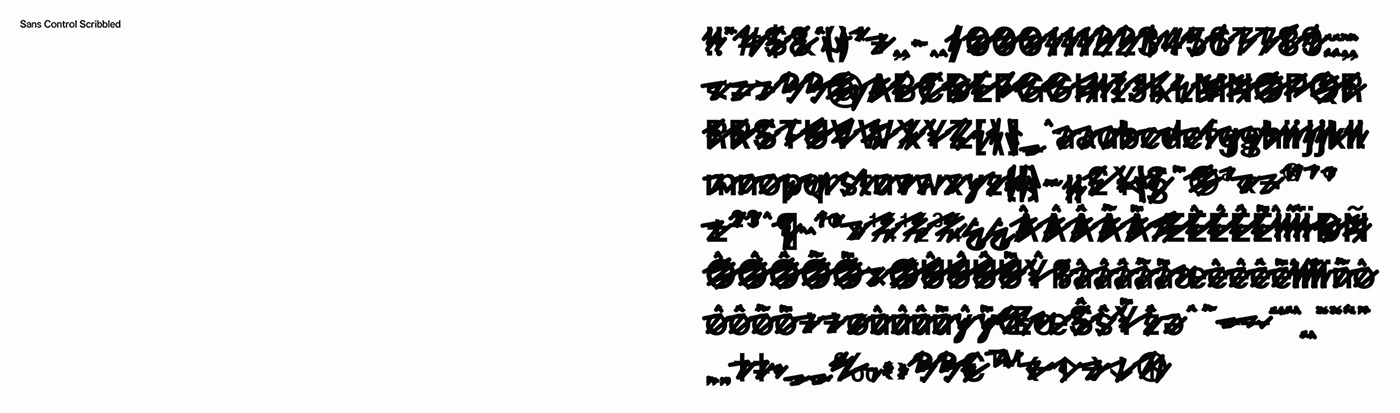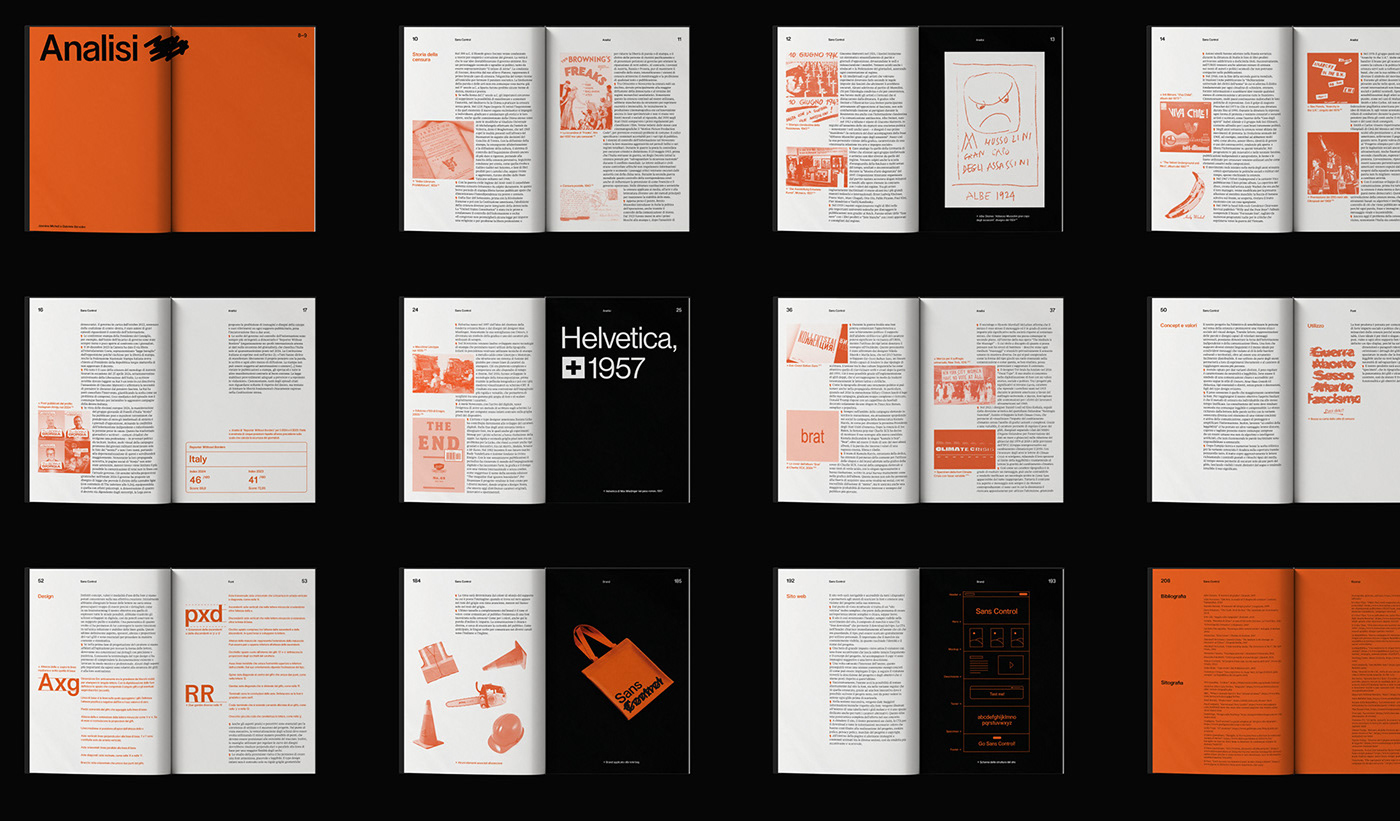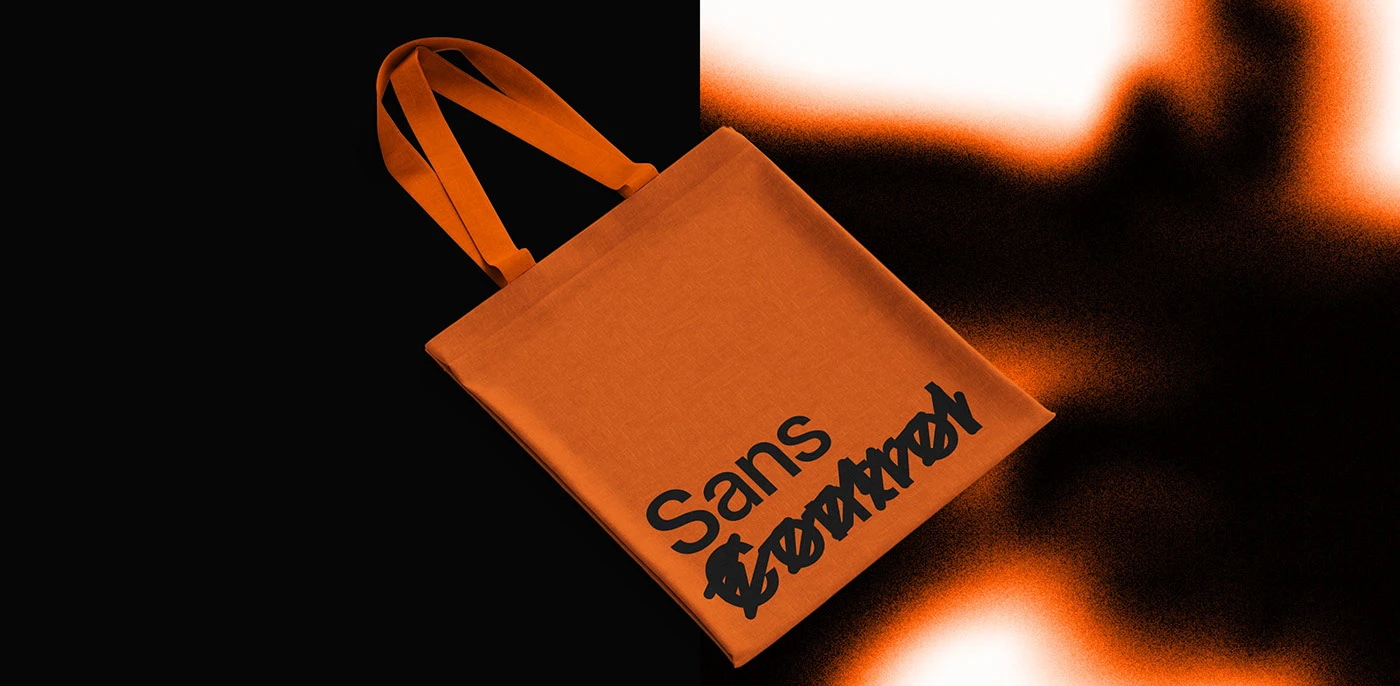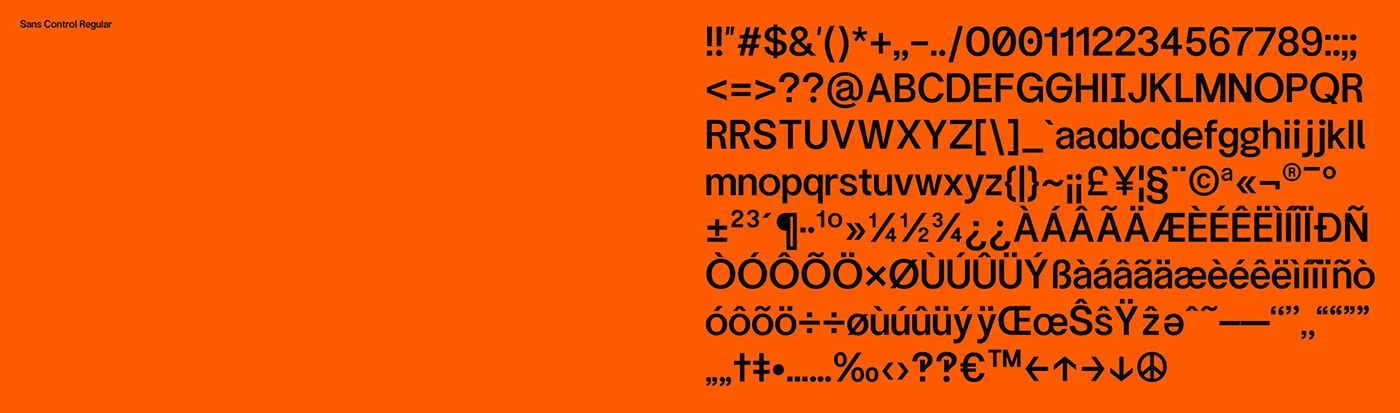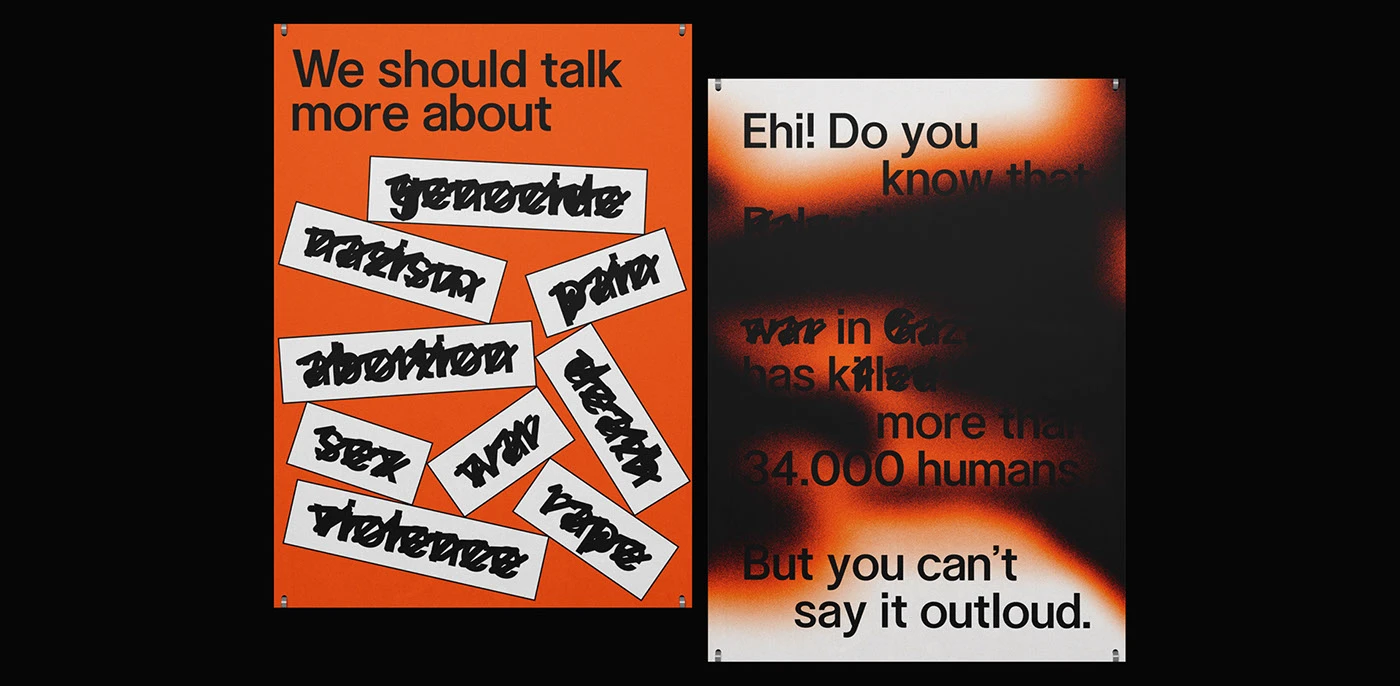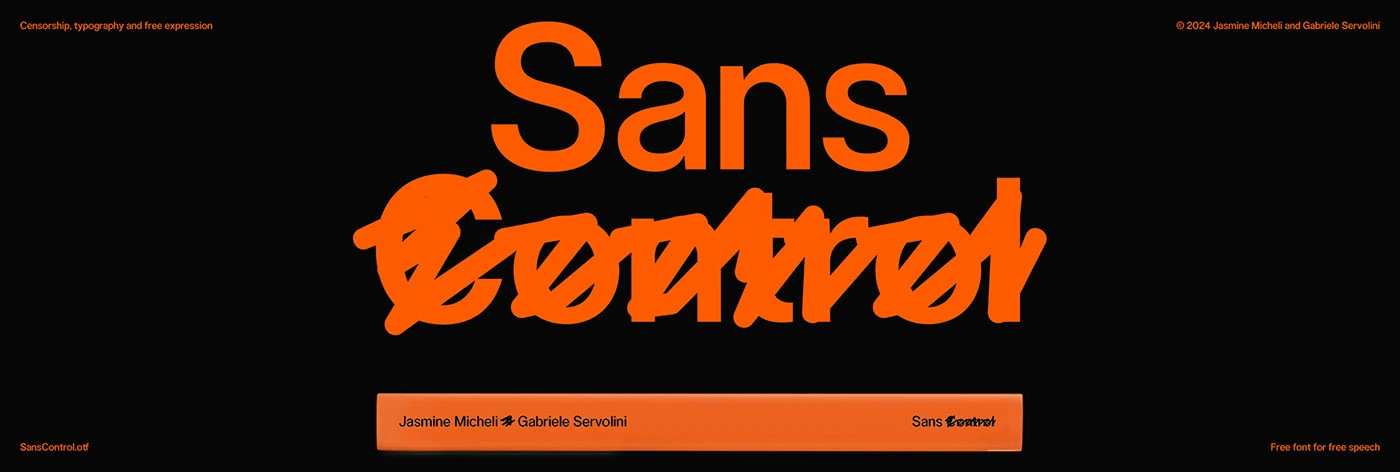
Font công nghiệp Pixel Surplus
Pixel Surplus vừa tung ra một bộ font chữ mang phong cách retro đầy táo bạo và hoàn toàn miễn phí, kết hợp những đường nét thiết kế thô mộc độc đáo từ Gabriele Servolini.
Hai nhà thiết kế Gabriele Servolini và Jasmine Micheli đã làm mới lại các asset font sans-serif kinh điển, tạo nên một bộ nhận diện thị giác cực kỳ nổi bật và dễ nhớ. Bộ font mới này sử dụng các đường nét dày dặn, phông nền hình học kết hợp cùng cấu trúc bố cục gọn gàng, tái hiện phong cách công nghiệp một cách vô cùng hiện đại. Nhờ sự kết hợp giữa hệ thống phân cấp typography hiện đại và các biểu tượng tùy chỉnh, bộ font trông vẫn rất gần gũi và dễ tiếp cận. Mọi yếu tố thiết kế đều cân bằng giữa sự tối giản về cấu trúc và cá tính năng động, mang đến một góc nhìn mới mẻ cho các biểu tượng trực quan cổ điển. Lựa chọn thẩm mỹ này tạo nên sự giao thoa giữa độ chính xác sắc nét và cảm giác ấm áp, đáp ứng đúng kỳ vọng về sự tin cậy của các designer ngày nay.
Bộ font miễn phí này không chỉ gói gọn trong không gian kỹ thuật số mà còn lấn sân sang cả các sản phẩm vật lý như poster in ấn, quần áo thời trang hay bao bì tùy chỉnh. Những món đồ này đều mang chung một phong cách thiết kế gọn gàng, giúp kết nối cộng đồng designer – những người luôn đề cao sự chính xác và bố cục chỉn chu. Phong cách thị giác này kết hợp hài hòa giữa layout trang tối giản và ảnh chụp sản phẩm trực quan. Các hình khối mô-đun đơn giản cùng độ dày nét đồng đều giúp tăng tính ứng dụng trên giao diện kỹ thuật số, tạo nên một phong cách đồng nhất và củng cố độ uy tín trong ngành thiết kế.
Sau cùng, bộ font mới đã đơn giản hóa cách khách hàng tương tác với nhận diện thương hiệu của doanh nghiệp. Các nhà thiết kế đã thành công trong việc tạo ra một trải nghiệm vừa thân thiện lại vừa cao cấp. Cấu trúc layout rõ ràng giúp các thông tin biên tập phức tạp trở nên dễ đọc, dễ hiểu ngay từ cái nhìn đầu tiên, biến kho dữ liệu này thành một công cụ cực kỳ hữu ích cho người dùng. Dự án này là minh chứng rõ ràng cho thấy thiết kế chiến lược có thể thay đổi một thương hiệu doanh nghiệp ra sao, giúp thương hiệu trở nên đáng tin cậy và kết nối tốt hơn với công chúng.
Pixel Surplus just dropped a bold, completely free retro font family that brings some seriously cool, raw design lines courtesy of Gabriele Servolini.
Designers Gabriele Servolini and Jasmine Micheli have given classic sans-serif assets a fresh spin, creating a super striking and memorable visual identity. This new font uses thick lines, geometric backgrounds, and clean layouts to give industrial style a thoroughly modern update. Thanks to a clever mix of modern typographic hierarchy and custom icons, the whole vibe stays totally approachable. Every design element perfectly balances structural minimalism with dynamic personality, offering a fresh take on classic visual icons. This aesthetic choice hits the sweet spot between sharp precision and a warm feel, checking all the boxes for what today’s designers look for in a reliable typeface.
This freebie isn’t just built for the digital world—it transitions seamlessly onto physical products like printed posters, apparel, and custom packaging. These items share a clean design language that builds an instant connection with the design community—folks who live for precision and crisp layouts. The visual style beautifully blends minimalist page layouts with clean product photography. Simple modular shapes and consistent stroke weights make it incredibly versatile for digital interfaces, creating a unified look that brings instant credibility to any design project.
Ultimately, this new font simplifies the way clients interact with a brand’s identity. The designers nailed the balance, crafting an experience that feels both friendly and high-end. Clear layout structures make complex editorial info a breeze to read at first glance, turning a massive dataset into an incredibly user-friendly tool. This project is a stellar example of how strategic design can transform a corporate brand, making it both trustworthy and deeply connected to its audience.